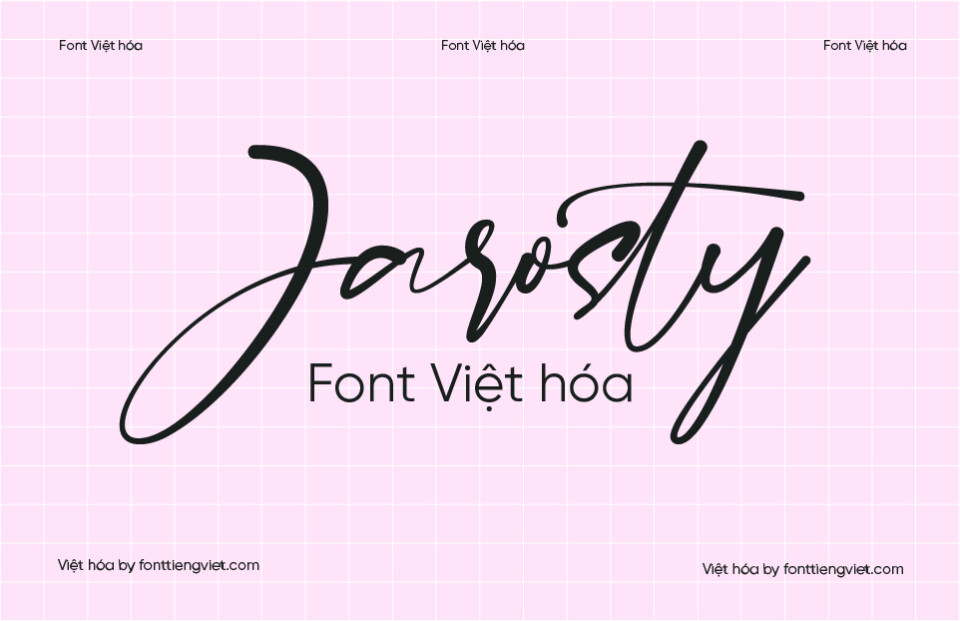
Tối ưu hóa thiết kế học đường với Font Việt hóa 1FTV VIP Jarosty
Trong thế giới thiết kế đồ họa và trình bày tài liệu học thuật, việc lựa chọn một bộ Font Chữ chất lượng cao, dễ đọc và thẩm mỹ là yếu tố then chốt quyết định sự thành công của một dự án. Đặc biệt đối với học sinh, sinh viên và các nhà thiết kế trẻ, một bộ font tối ưu hóa sẽ giúp các bài thuyết trình, luận văn tốt nghiệp hoặc tài liệu ôn thi trở nên chuyên nghiệp hơn. Gần đây, cộng đồng người dùng Việt Nam đang xôn xao về một cái tên đặc biệt: Font Việt hóa 1FTV VIP Jarosty. Đây không chỉ là một bộ font thông thường; nó là sự kết hợp hoàn hảo giữa phong cách thiết kế độc đáo và khả năng hỗ trợ tiếng Việt hoàn chỉnh, đáp ứng mọi yêu cầu khắt khe nhất trong môi trường học đường và sáng tạo.
Khám Phá Sự Tuyệt Vời Của Font Việt hóa 1FTV VIP Jarosty
Bộ font này được mệnh danh là “VIP” không chỉ vì vẻ ngoài độc đáo mà còn vì quy trình Việt hóa tỉ mỉ, giúp nó hiển thị chuẩn xác tất cả các dấu tiếng Việt, bao gồm cả các ký tự phức tạp và các biến thể chữ. Thiết kế của Jarosty thường mang đến cảm giác hiện đại nhưng vẫn giữ được nét thanh lịch, rất phù hợp cho các bìa sách, poster dự án khoa học, hoặc thậm chí là các ấn phẩm quảng bá sự kiện của trường. Sự chú trọng vào chi tiết trong quá trình Việt hóa đảm bảo rằng người dùng có thể gõ văn bản tiếng Việt mà không gặp phải bất kỳ lỗi hiển thị hay mất nét nào, điều mà nhiều bộ font quốc tế khác thường mắc phải. Đối với những dự án đòi hỏi sự chuyên nghiệp cao như luận án tốt nghiệp hay báo cáo thực tập, việc sử dụng một bộ font chuẩn như Font Việt hóa 1FTV VIP Jarosty sẽ nâng tầm chất lượng trình bày lên đáng kể. Hơn nữa, độ tương thích cao của font với các phần mềm thiết kế và soạn thảo văn bản phổ biến như Microsoft Office hay Adobe Creative Suite là một lợi thế lớn, giúp quá trình làm việc của người dùng trở nên suôn sẻ và hiệu quả.
Tại Sao 1FTV VIP Jarosty Lại Được Giới Học Sinh, Sinh Viên Yêu Thích?
Lý do chính khiến 1FTV VIP Jarosty trở thành lựa chọn hàng đầu trong giới trẻ là tính đa dụng và khả năng đọc tuyệt vời (readability). Khi phải xử lý một lượng lớn thông tin để chuẩn bị cho các kỳ thi quan trọng, từ thi tốt nghiệp trung học phổ thông đến các bài kiểm tra đầu vào đại học, việc có một tài liệu được trình bày rõ ràng là vô cùng quan trọng. Bộ font này cung cấp các nét chữ rõ ràng, độ dày vừa phải, giúp mắt không bị mỏi khi đọc lâu. Các tài liệu ôn tập, sách giáo trình tự biên soạn hay thậm chí là đề thi thử đều được hưởng lợi từ sự rõ ràng này. Hơn nữa, với các sinh viên chuyên ngành thiết kế đồ họa, đây là một tài sản quý giá để tạo ra các typography ấn tượng, các logo cá nhân hoặc các mẫu thiết kế portfolio nổi bật. Việc sở hữu và sử dụng Font Việt hóa 1FTV VIP Jarosty giúp các bạn học sinh, sinh viên tạo ra sự khác biệt và thể hiện sự đầu tư nghiêm túc vào sản phẩm học tập của mình.
Hướng Dẫn Sử Dụng Font Trong Các Dự Án Học Tập và Đồ Án Tốt Nghiệp
Công Nghệ Việt Hóa Đằng Sau Bộ Font Chữ Đặc Biệt Này
Quá trình Việt hóa một bộ font là một nghệ thuật đòi hỏi sự chính xác cao và hiểu biết sâu sắc về ngôn ngữ. Đối với Font Việt hóa 1FTV VIP Jarosty, các chuyên gia đã tiến hành điều chỉnh cẩn thận từng cặp ký tự (kerning) và tối ưu hóa hiển thị trên các kích cỡ khác nhau (hinting). Điều này đảm bảo rằng dù bạn sử dụng font ở kích thước 12pt trên văn bản in hay 48pt trên một banner kỹ thuật số, chất lượng hiển thị vẫn sắc nét và không bị biến dạng, giữ nguyên được ý đồ thiết kế ban đầu. Việc tuân thủ chuẩn Unicode mở rộng (Extended Unicode) là một điểm mạnh lớn, cho phép font tương thích hoàn hảo với mọi hệ điều hành và mọi ứng dụng phần mềm hiện đại, từ các công cụ văn phòng cơ bản đến các phần mềm thiết kế chuyên nghiệp. Không chỉ dừng lại ở việc thêm dấu, quá trình này còn bao gồm việc tinh chỉnh khoảng cách dòng (leading) và khoảng cách chữ (tracking) để tối đa hóa khả năng đọc tiếng Việt, một yếu tố cực kỳ quan trọng cho các tài liệu học thuật dài hơi. Sự đầu tư kỹ lưỡng vào công nghệ Việt hóa chính là yếu tố biến Jarosty thành một tài sản “VIP” không thể thiếu cho những người làm việc nghiêm túc với ngôn ngữ tiếng Việt và mong muốn đạt được chất lượng hình ảnh cao nhất.
Tóm lại, việc đầu tư vào các công cụ chất lượng như Font Việt hóa 1FTV VIP Jarosty là bước đi thông minh cho bất kỳ ai đang theo đuổi sự hoàn hảo trong thiết kế và trình bày tài liệu. Đây là giải pháp typography tối ưu, mang lại sự chuyên nghiệp, dễ đọc và tính thẩm mỹ cao cho các dự án học đường và cá nhân. Nếu bạn đang tìm kiếm một bộ Font Chữ có thể thay đổi hoàn toàn cách bạn truyền tải thông điệp, Jarosty chính là câu trả lời. Hãy trải nghiệm ngay hôm nay để thấy sự khác biệt mà một bộ font VIP, đã được Việt hóa cẩn thận, có thể mang lại cho các tài liệu học tập và đồ án thiết kế của bạn.